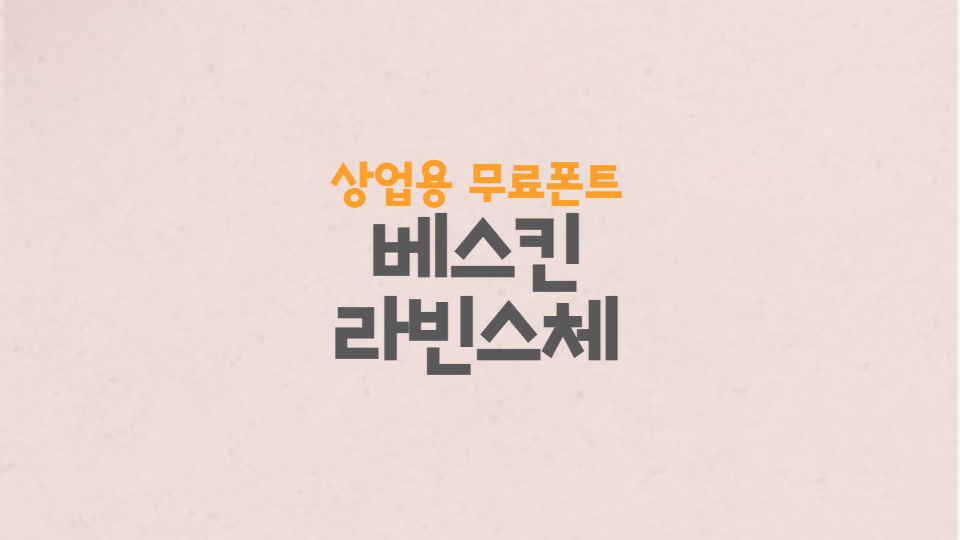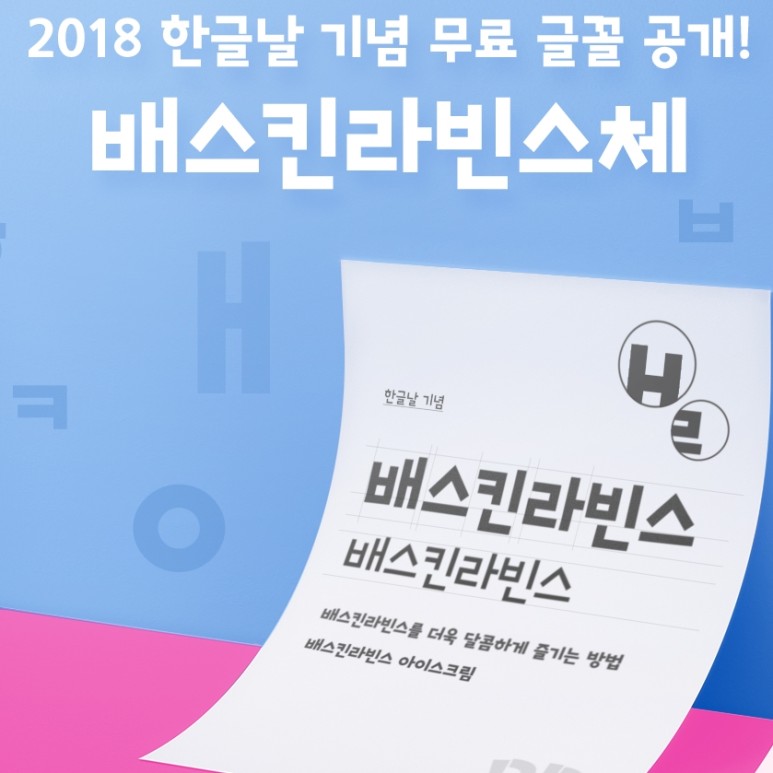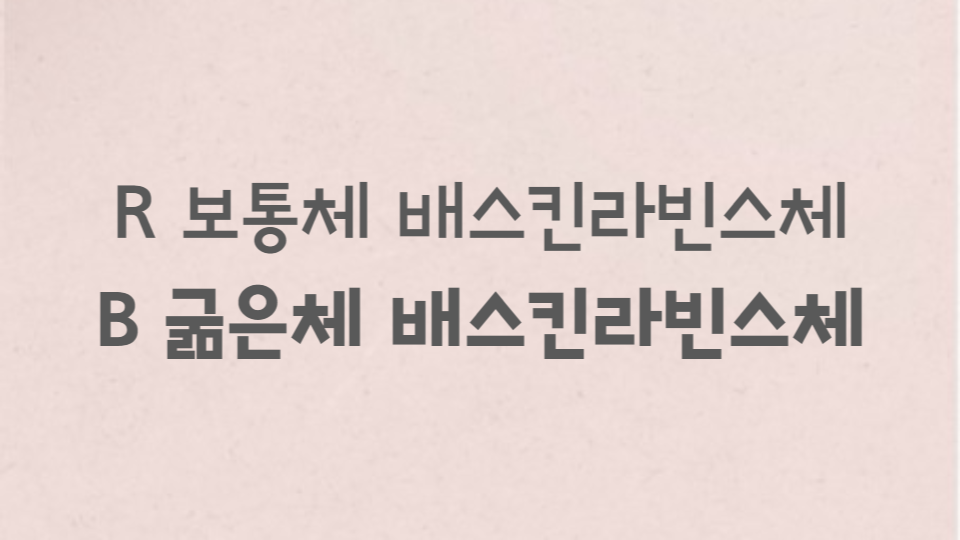
배스킨라빈스체 무료배포
2018년 한글날 기념으로 무료로 글꼴을 공개하고 제공해서 지금까지 많은 사랑을 받고 있는 디자인 폰트입니다. 배스킨라빈스체라고 해서 31가지 맛 아이스크림의 로고와 같은 폰트로 디자인되어 있습니다. 고딕체로 간결한 느낌을 주고 자음과 모음의 높낮이와 가로 폭을 다양하게 조절해서 리듬감을 표현한 발랄한 폰트입니다. 상업적으로 사용이 가능한 폰트로 변형해서 재배포하는 것은 금지되어 있습니다. 자세한 내용은 아래 라이선스 안내를 확인하시기 바랍니다.
배스킨라빈스 폰트는 일반체와 굵은 체가 배포되고 있습니다.